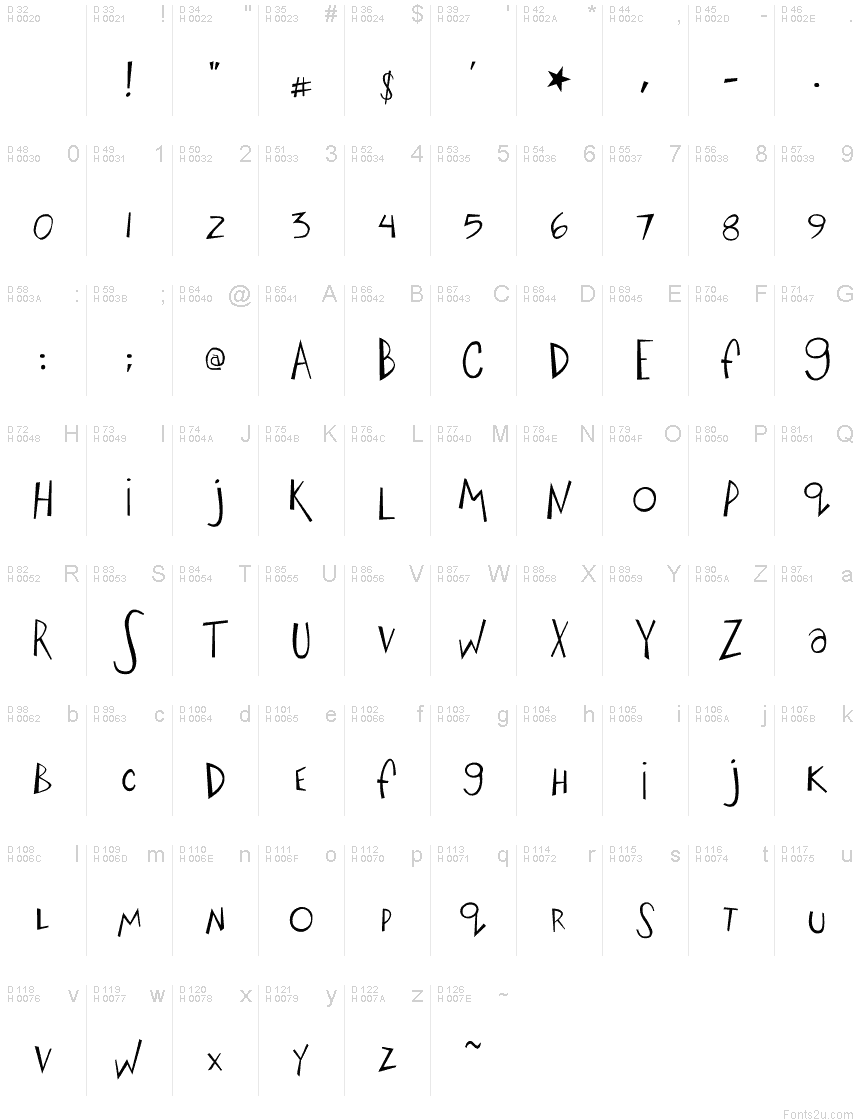
Big Fish Ensemble autorstwa Johna Martza to bezpłatny, komiksowy krój typu display. Jego urok tkwi w smukłym, ręcznie szkicowanym rytmie: cienkich, tuszowych pociągnięciach, luźnych odstępach i zachwycająco nierównym „skakaniu” liter, które sprawia wrażenie bazgrołów w notatniku, a nie projektu na siatce. Ta niekonwencjonalna elegancja nadaje nagłówkom prawdziwej osobowości, nie wprowadzając przy tym chaosu.
Big Fish Ensemble sprawdza się doskonale w tytułach komiksów, zaproszeniach na przyjęcia dla dzieci, plakatach szkolnych, zinach, niezależnych gadżetach, zabawnych opakowaniach czy grafikach do mediów społecznościowych w stylu scrapbookingowym. Ten darmowy font najlepiej prezentuje się w większych rozmiarach, gdzie jego ażurowa tekstura ma przestrzeń, by wybrzmieć. Połącz go z prostym bezszeryfowym krojem, takim jak Helvetica lub Arial, aby zachować przejrzystość układu i pozwolić, by ten nietuzinkowy literniczy styl nadał całości charakteru.